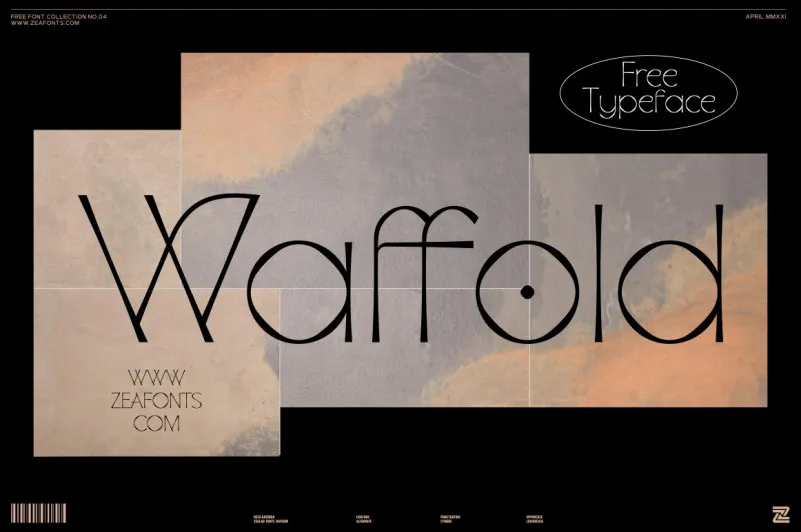
Waffold Sans Serif Font – Download Grátis
Descubra Waffold Sans Serif Font, uma elegante tipografia de sans serif que se destaca no mundo dos materiais modernos e sofisticados. Perfeita para marcas de alta-end, logomarcas de boutique, roupas, joias e muito mais, essa fonte tem dois caracteres alternativos ou ligantes em cada capital, criando um design vibrante e arrojado. O design do Waffold é caracterizado por uma elegância clássica e uma fluidez gráfica impecável. Estes elementos proporcionam um toque único ao seu design, aumentando assim a visualização de qualquer elemento de marca que use essa fonte. Perfeito para empresas que valorizam uma presença estilosa e sofisticada, Waffold é o tipo certo para sua identidade visual. Ele é como um bom amigo: sempre está presente, mas nunca esgota seu encanto. Seja você um designer ou profissional de branding, não hesite em experimentar a experiência de trabalhar com Waffold – ele fará sua marca brilhar ainda mais. Combinado ao design do 99designs que é famoso pelo nível alto e criatividade, essa fonte se torna uma verdadeira joia para qualquer tipo de projeto visual que busque um toque de sofisticação e modernidade.